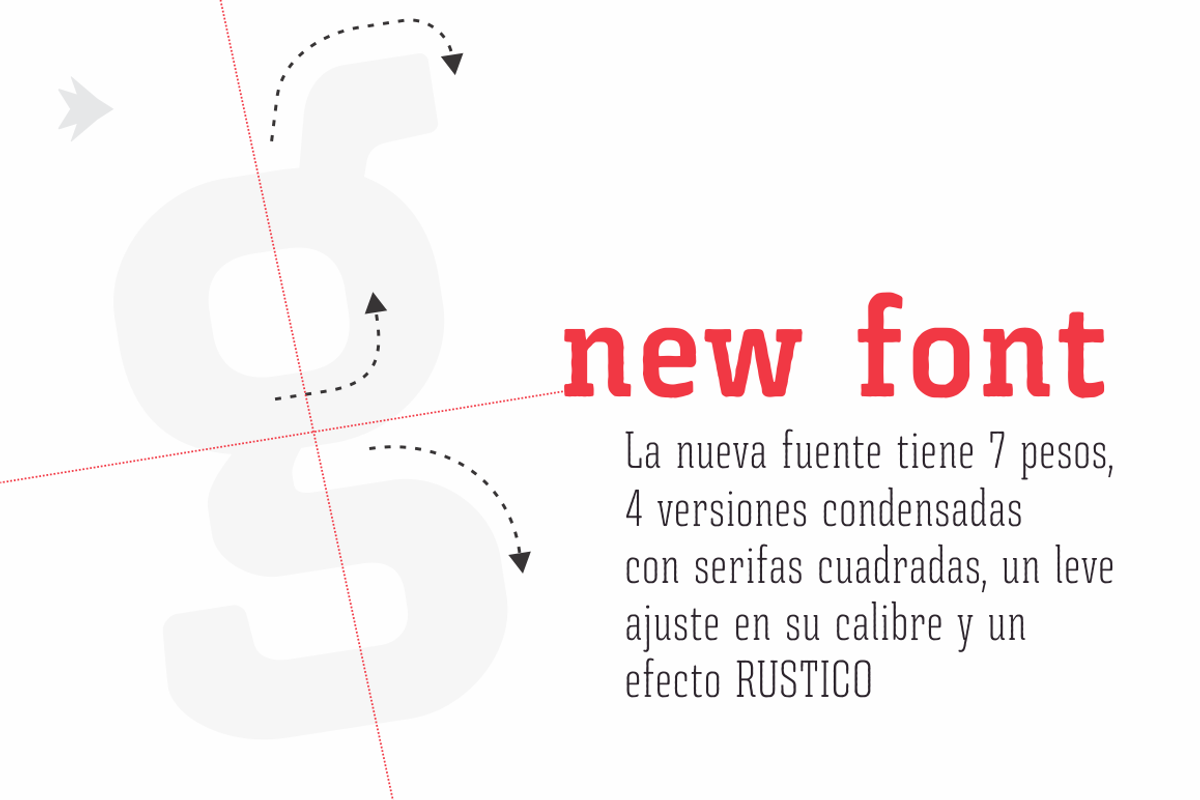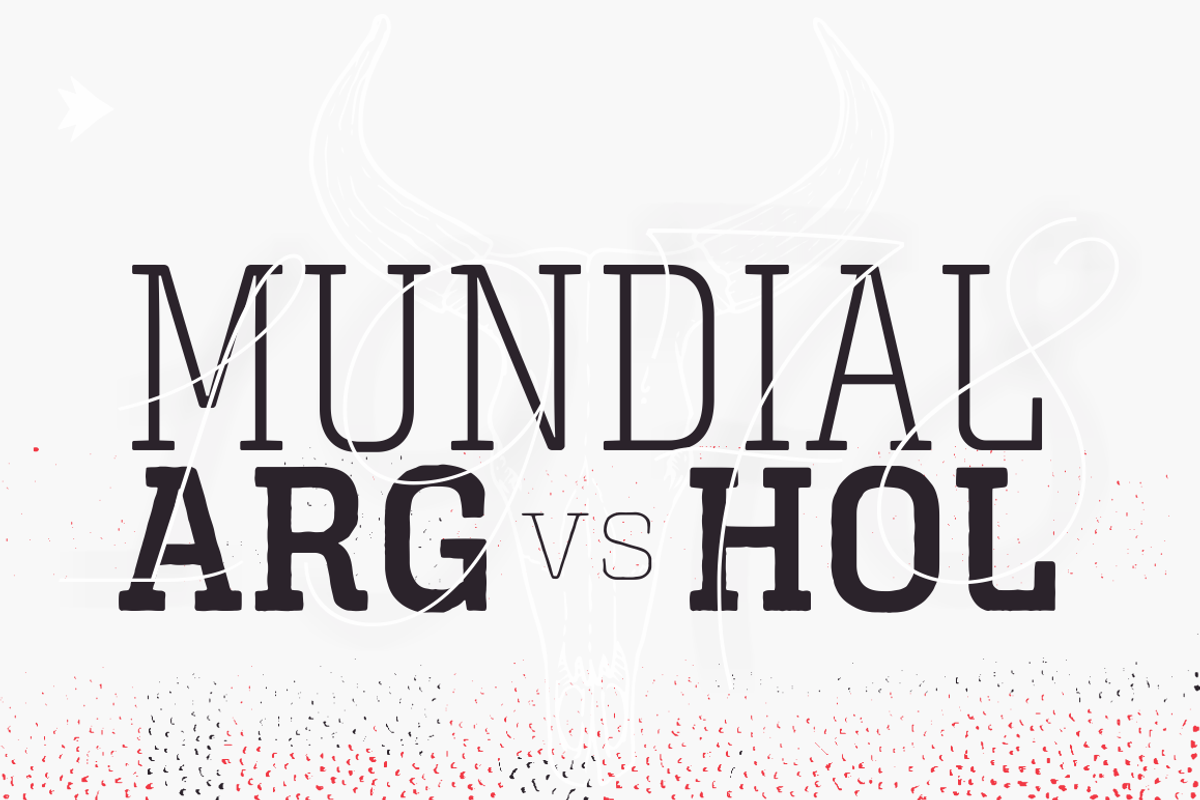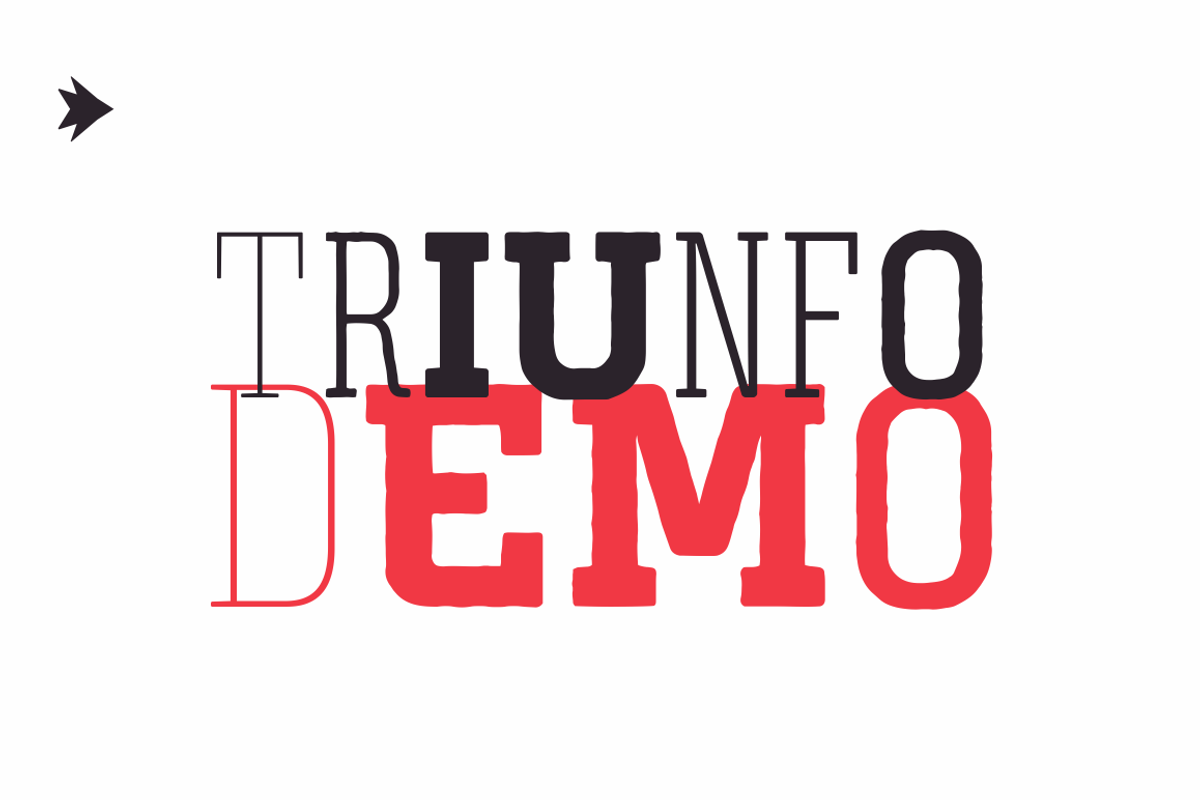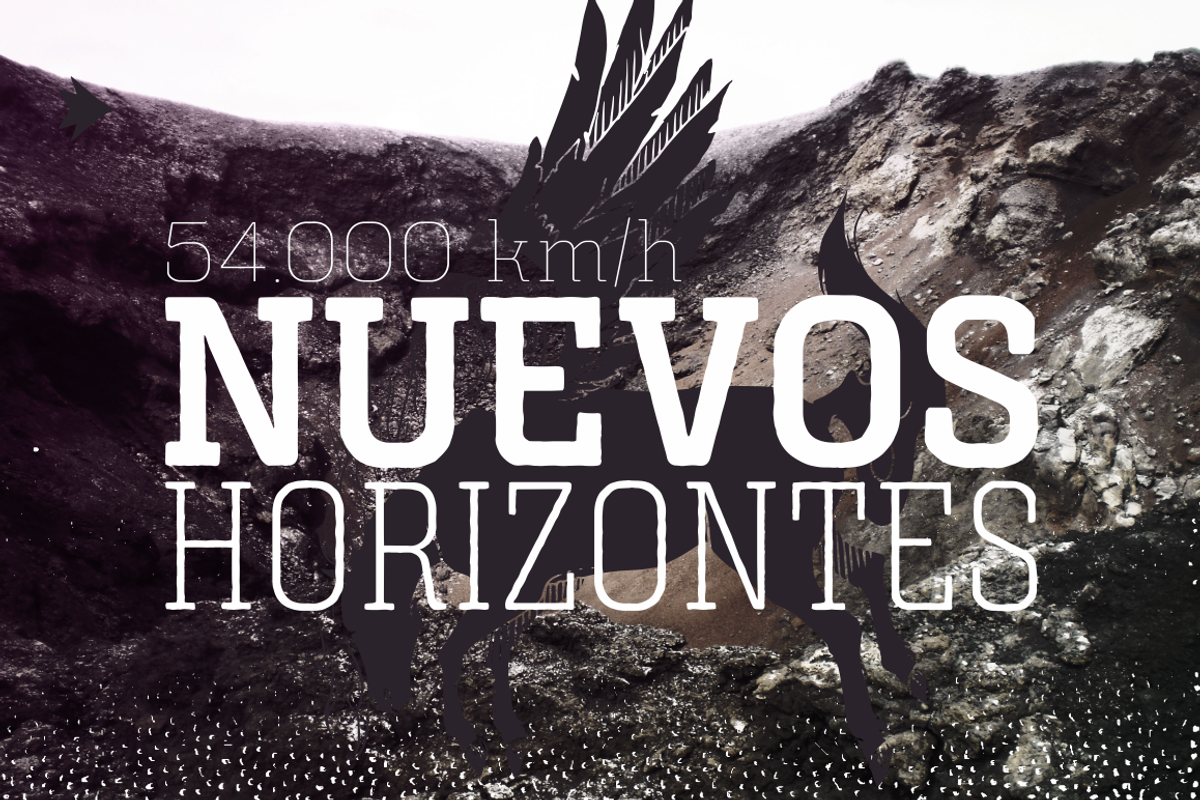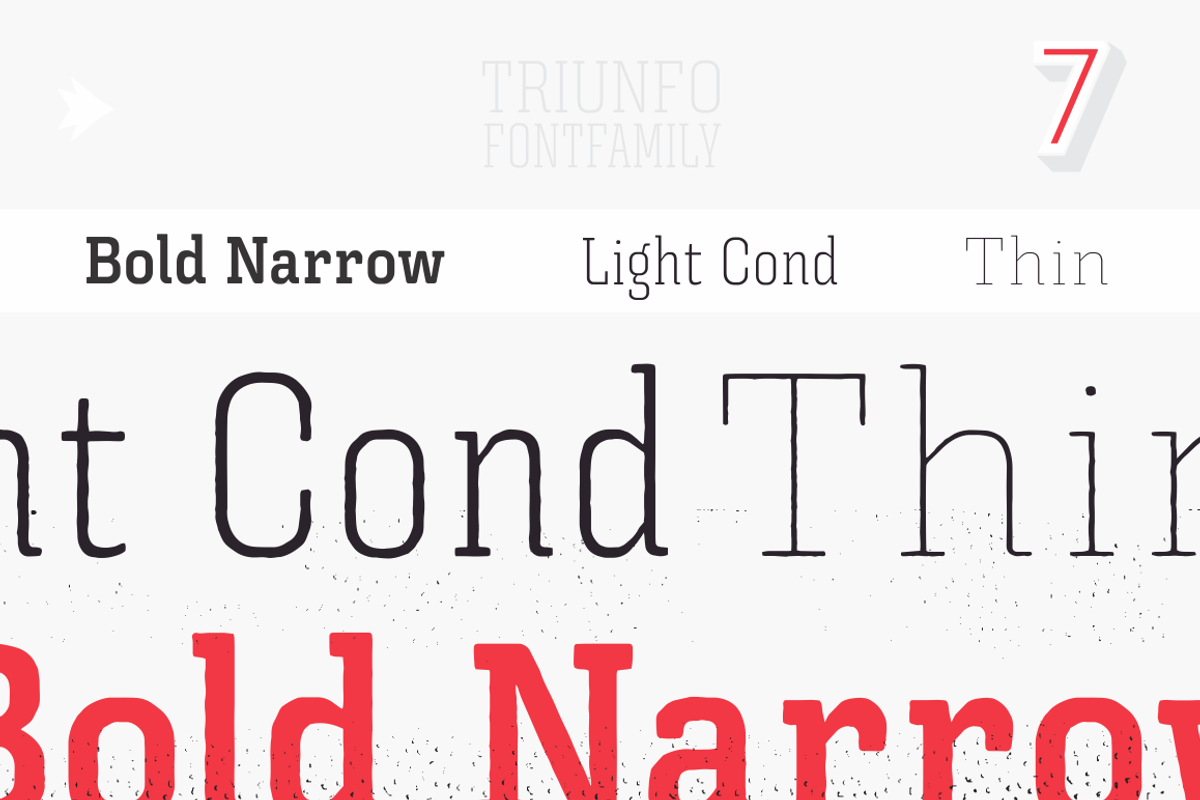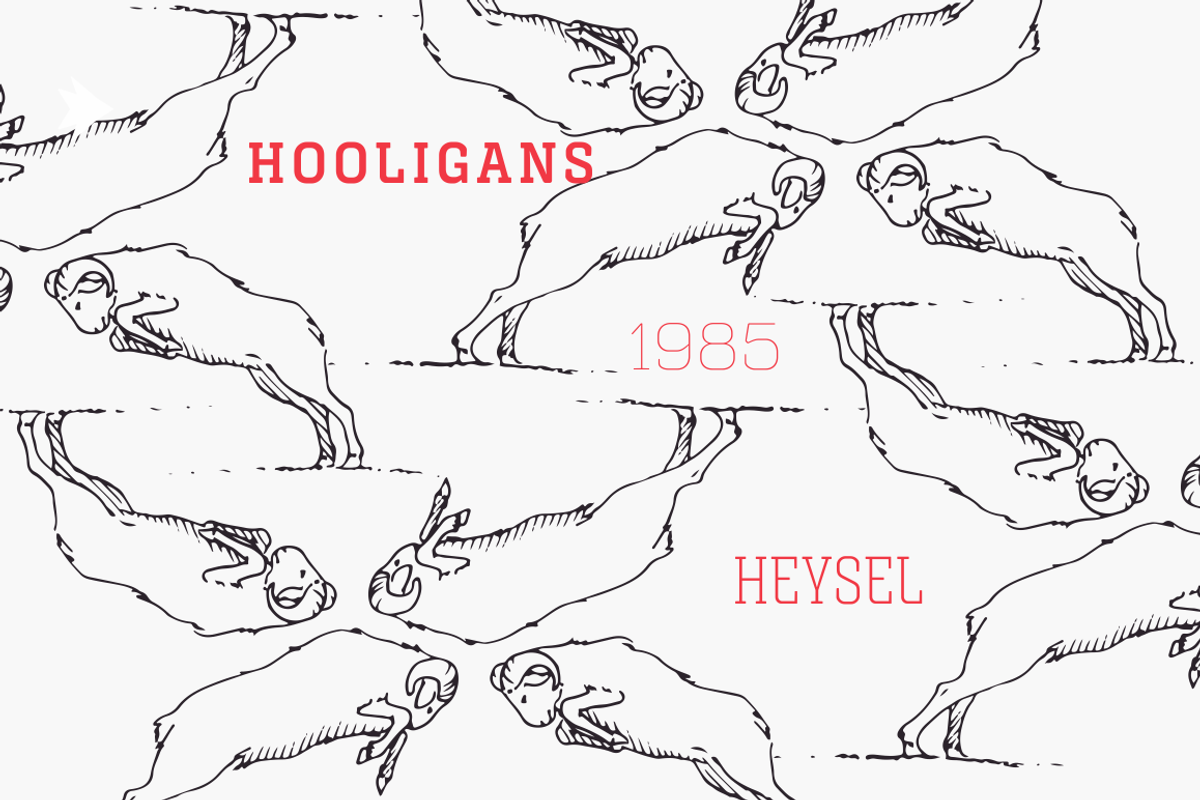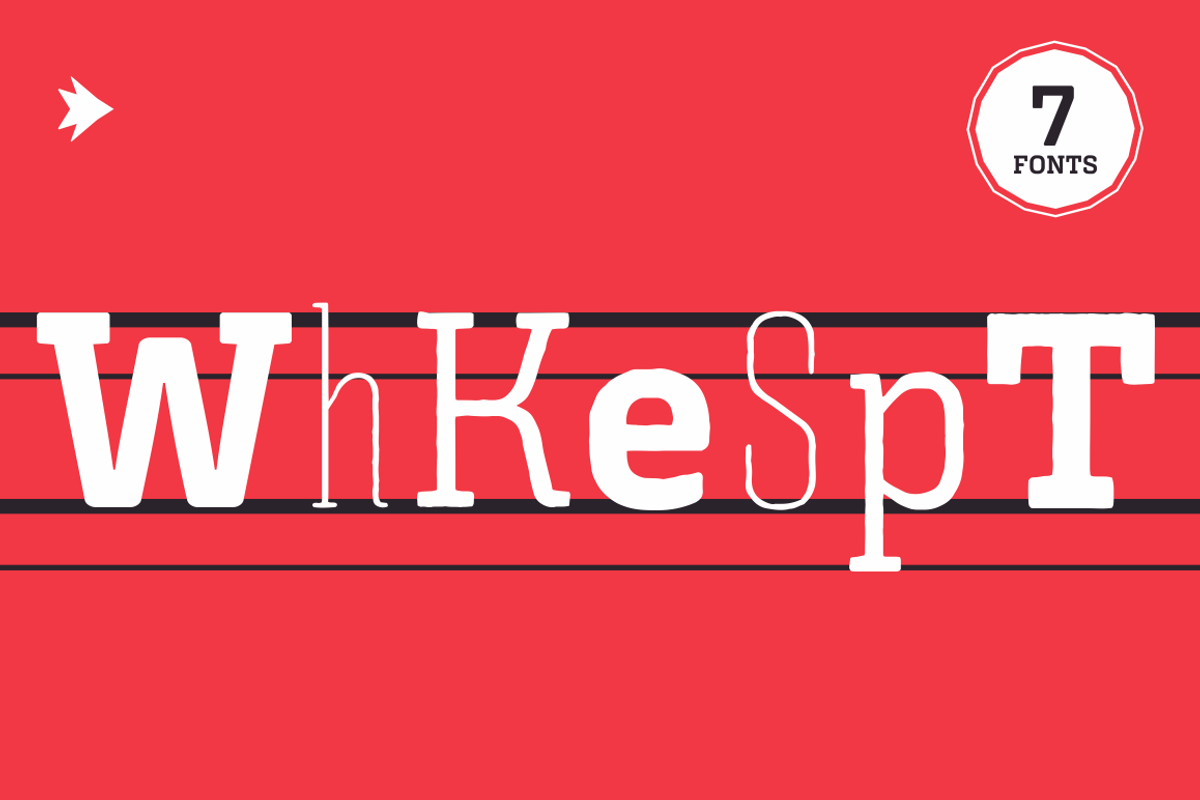
La familia tipográfica TRIUNFO diseñada junto a Manuel Corradine en CorradineFonts, tiene varios pesos que permiten una diversidad maravillosa a la hora de usarla ademas su versatilidad aumenta en el momento que descubres que sus letras incluyen variedad de ancho lo cual la hace única y especial.
The typeface family TRIUNFO designed feat Manuel Corradine in CorradineFonts, has several weights that allow a wonderful diversity when it is used and its versatility increases when you discover that its letters include variety of width which makes it unique and special.